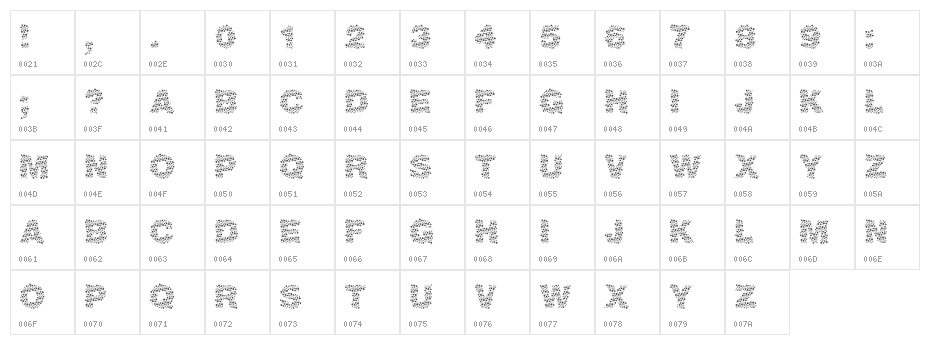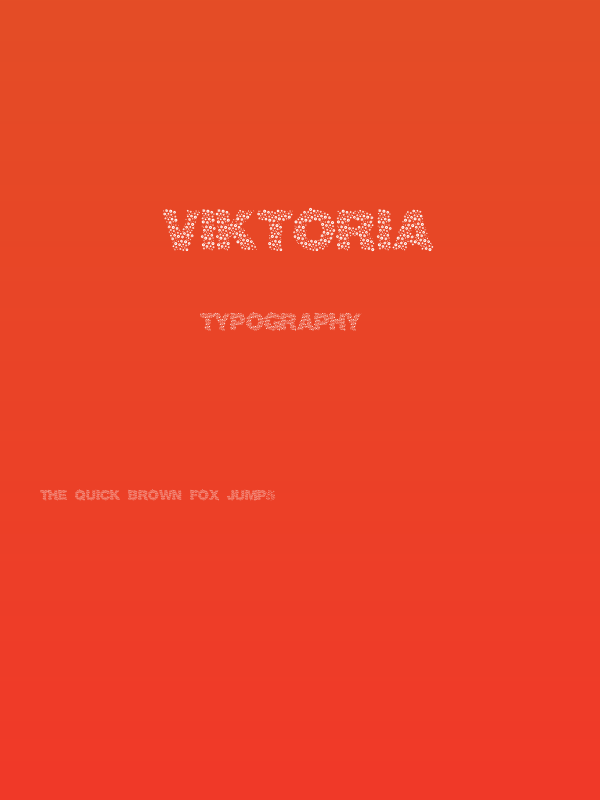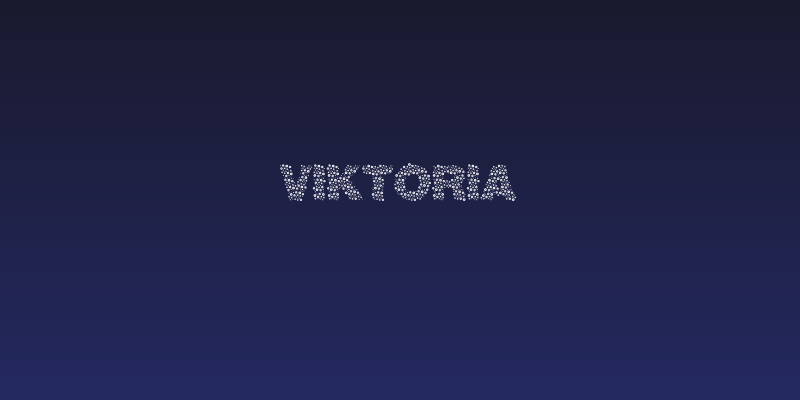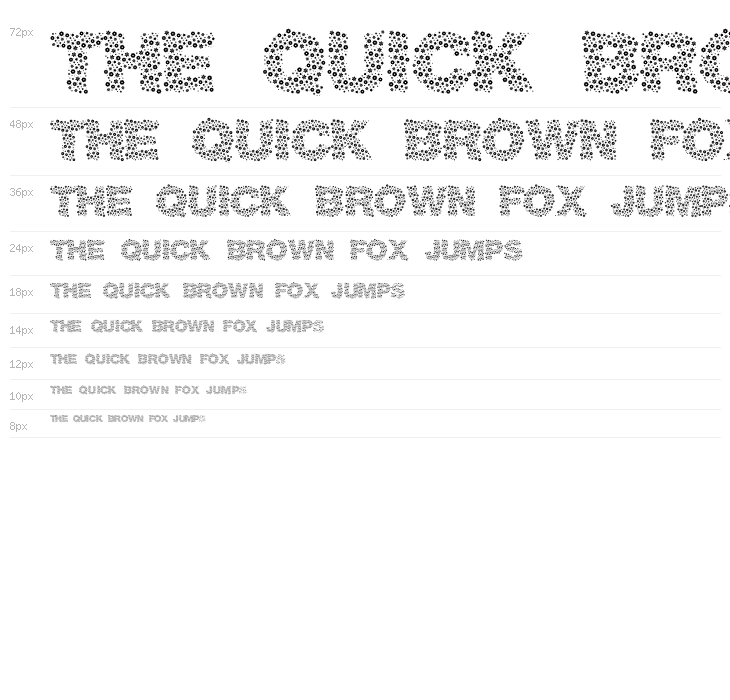
viktoria Font
| Vorgeschlagene Projekte | This font is perfect for children's book covers, party invitations, playful branding, and any project that requires a fun and whimsical touch. |